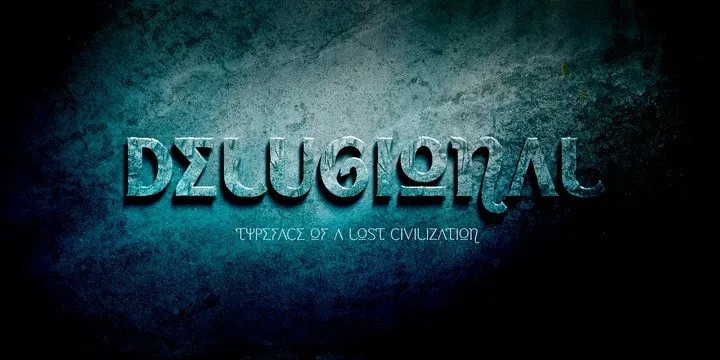
A fonte Delugional é uma combinação fascinante de estilos vintage e modernos que a tornam perfeita para qualquer estilo de design. Combina uma alfabeto imaginário inspirado no grego com influências clássicas latinas, criando um visual único que se adequa perfeitamente à maioria dos projetos gráficos. Este é o versão demo da fonte Regular da família Delugional, composta por dois pesos: Regular e Bold. Ela pode ser usada em uma ampla variedade de projetos criativos e mitológicos ou fantásticos, como capas de livros, jogos ou títulos de filmes. Na versão completa, a fonte oferece recursos OpenType avançados, incluindo alternativas estilísticas e ligaturas discretas, bem como símbolos adicionais que podem ser usados em casos especiais, como o mapa do Antilhas estilizado em substituição aos caracteres de “O” maiúsculos da fonte estilo 02. Delugional é a escolha perfeita para projetos que exigem um toque único e uma atmosfera misteriosa, tanto na identidade visual quanto no design editorial. Seja você um designer gráfico profissional ou iniciante, Delugional certamente vai adicionar um elemento especial aos seus trabalhos de arte.